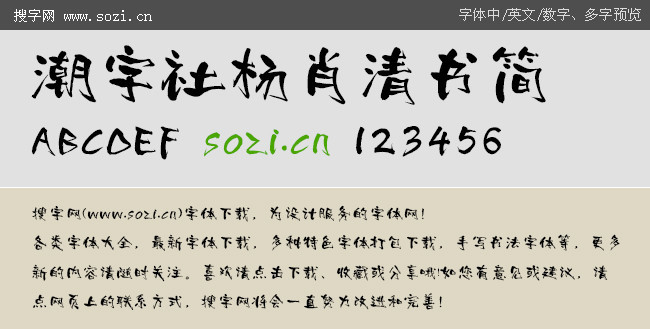
潮字社杨肖清书简
搜字网提供一款潮字社杨肖清书简中文字体下载,潮字社杨肖清书字体是由锐字工房开发设计的一款中文手写字体,该字体笔触粗细适中,整个字体非常流畅自然,大气中还带一些时尚,适用于书籍封面设计、报刊标头设计,包装设计,海报设计等广告应用。(此款为个人非商用版,如需商用请联系锐字工房购买)
• 风格类别: 手写书法体